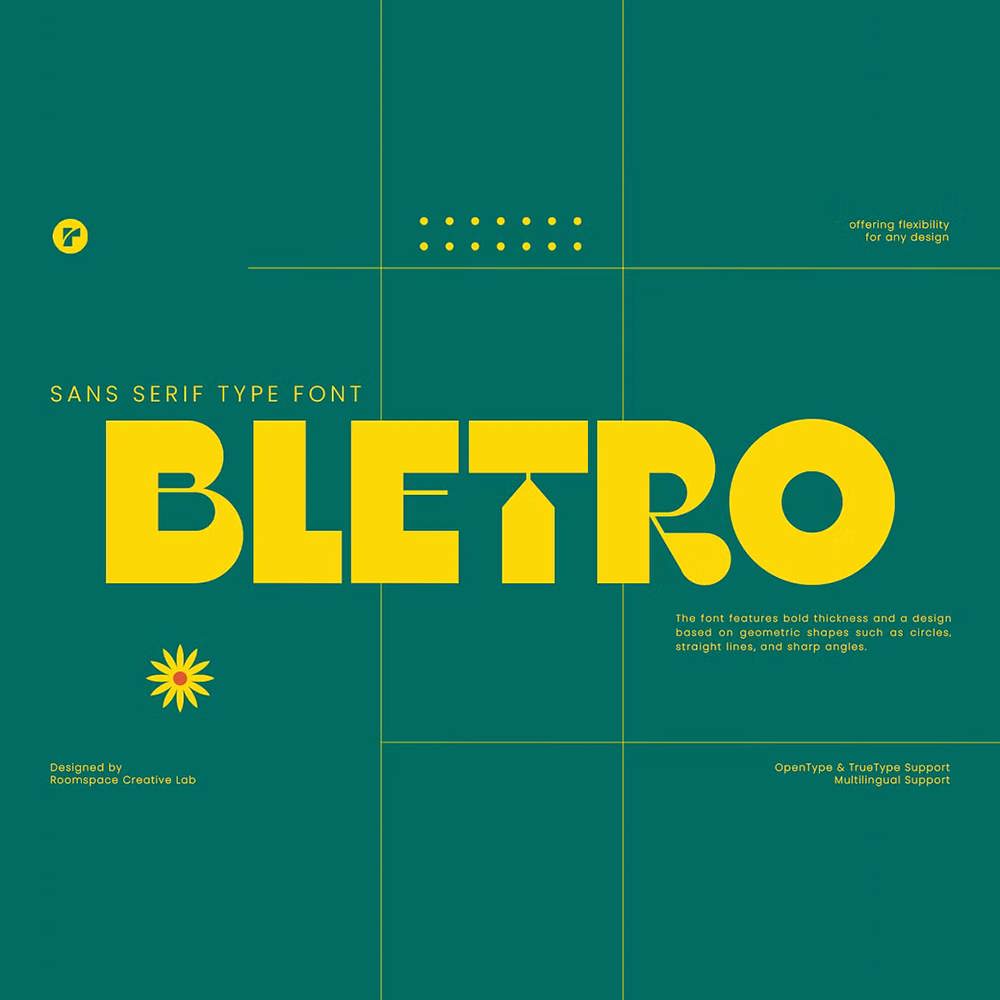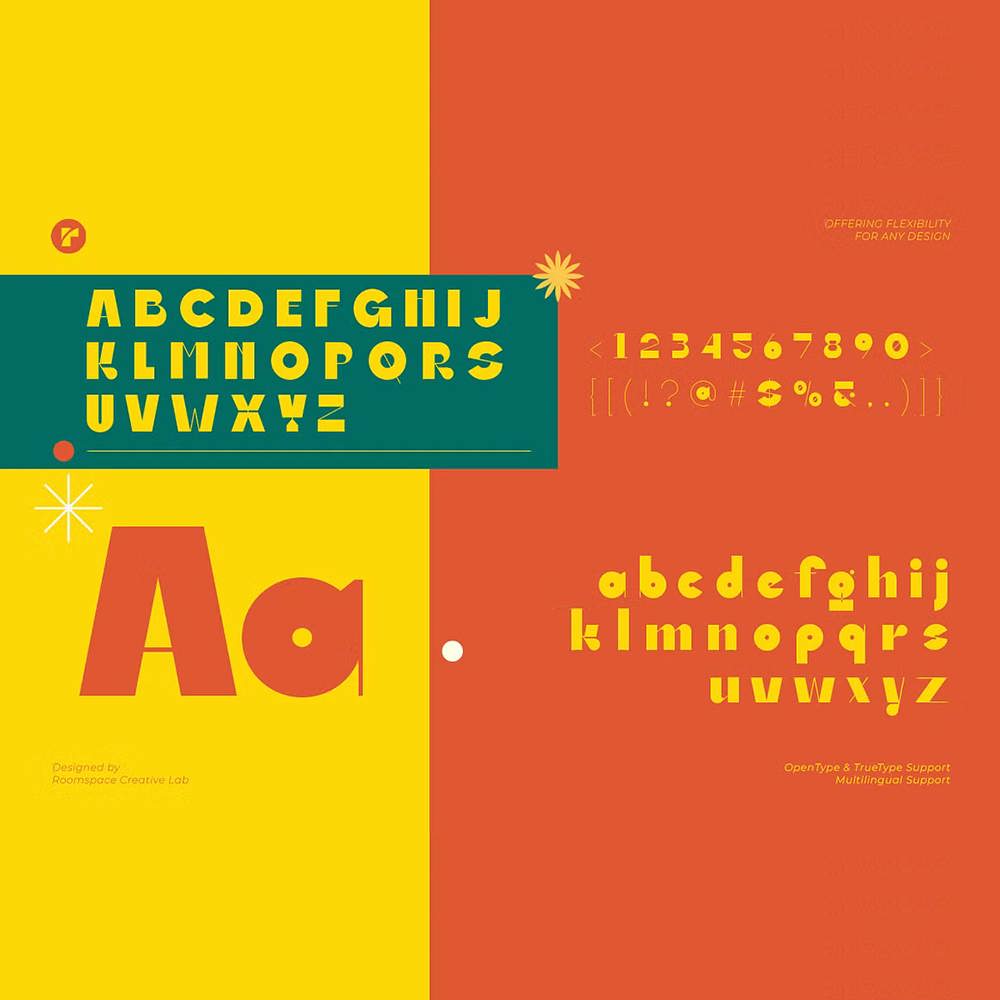
دانلود فونت انگلیسی Bletro Font
فونت پرمیوم و انگلیسی Bletro Font یک فونت نمایشی خیرهکنندهی سنس سریف است که به طور کامل زیباییشناسی مدرن و رترو را متعادل میکند. این فونت با اشکال هندسی، ضخامت پررنگ و زوایای تیز طراحی شده است و جذابیت منحصر به فردی را به نمایش میگذارد که برای ایجاد تیترهای چشمنواز، لوگوها، مواد برندسازی و پوسترهای خلاقانه ایدهآل است. چه به دنبال یک زیباییشناسی قدیمی باشید و چه یک فونت تمیز و مدرن، بلترو به طور یکپارچه برای ارتقاء هر پروژه طراحی سازگار میشود. این فونت پررنگ، ظرافت و طراحی فونت شیک را با هم ترکیب میکند و آن را برای طراحی گرافیک، تایپوگرافی تزئینی یا حتی پروژههای فونت مینیمالیستی ایدهآل میکند. تطبیقپذیری آن در کاربردهایی مانند فونت برندسازی، فونت پوستر یا فونت تیتر برای کمپینهای رسانههای اجتماعی میدرخشد.
مزایای استفاده از فونت لاتین Bletro چیست؟